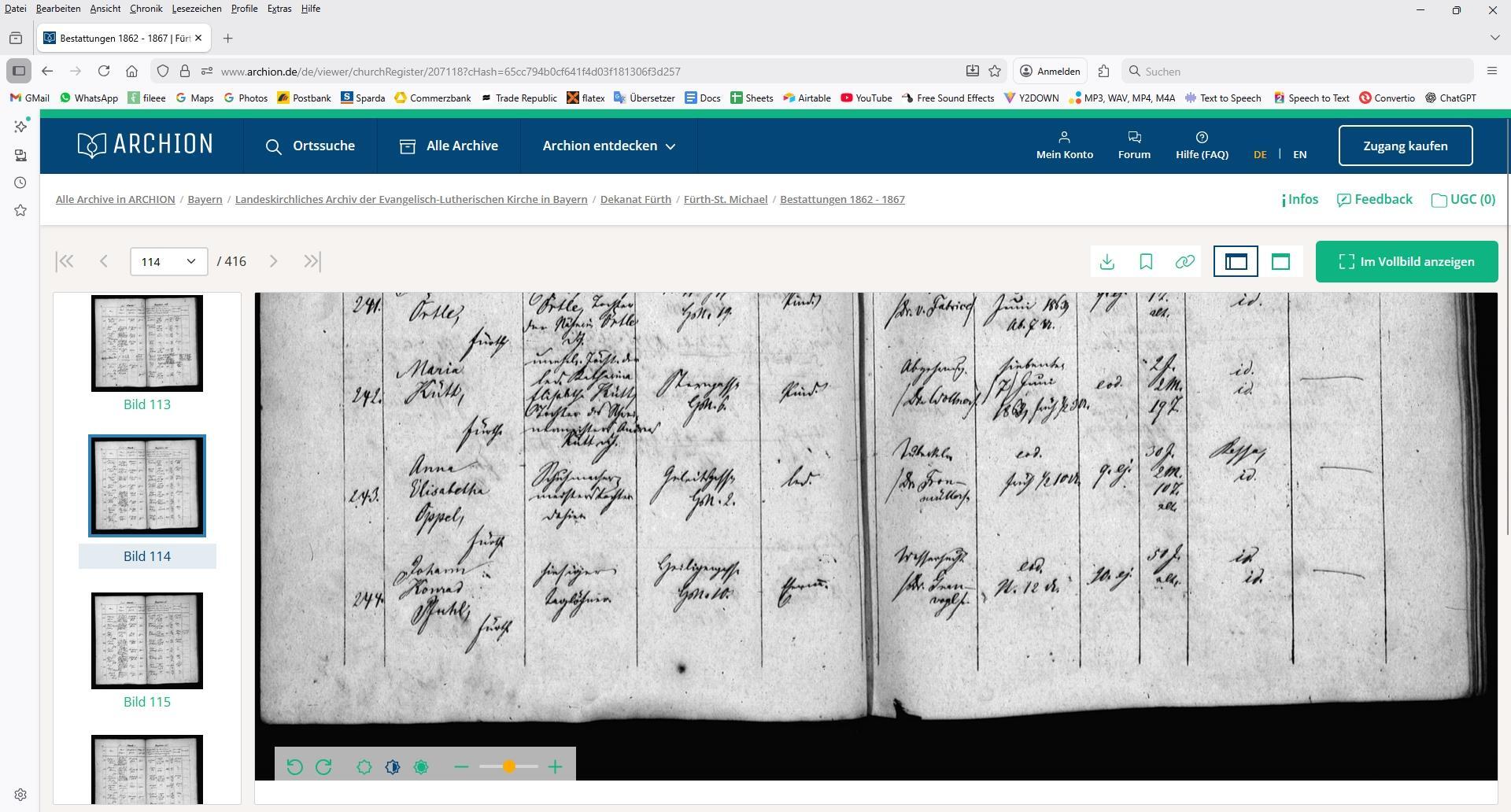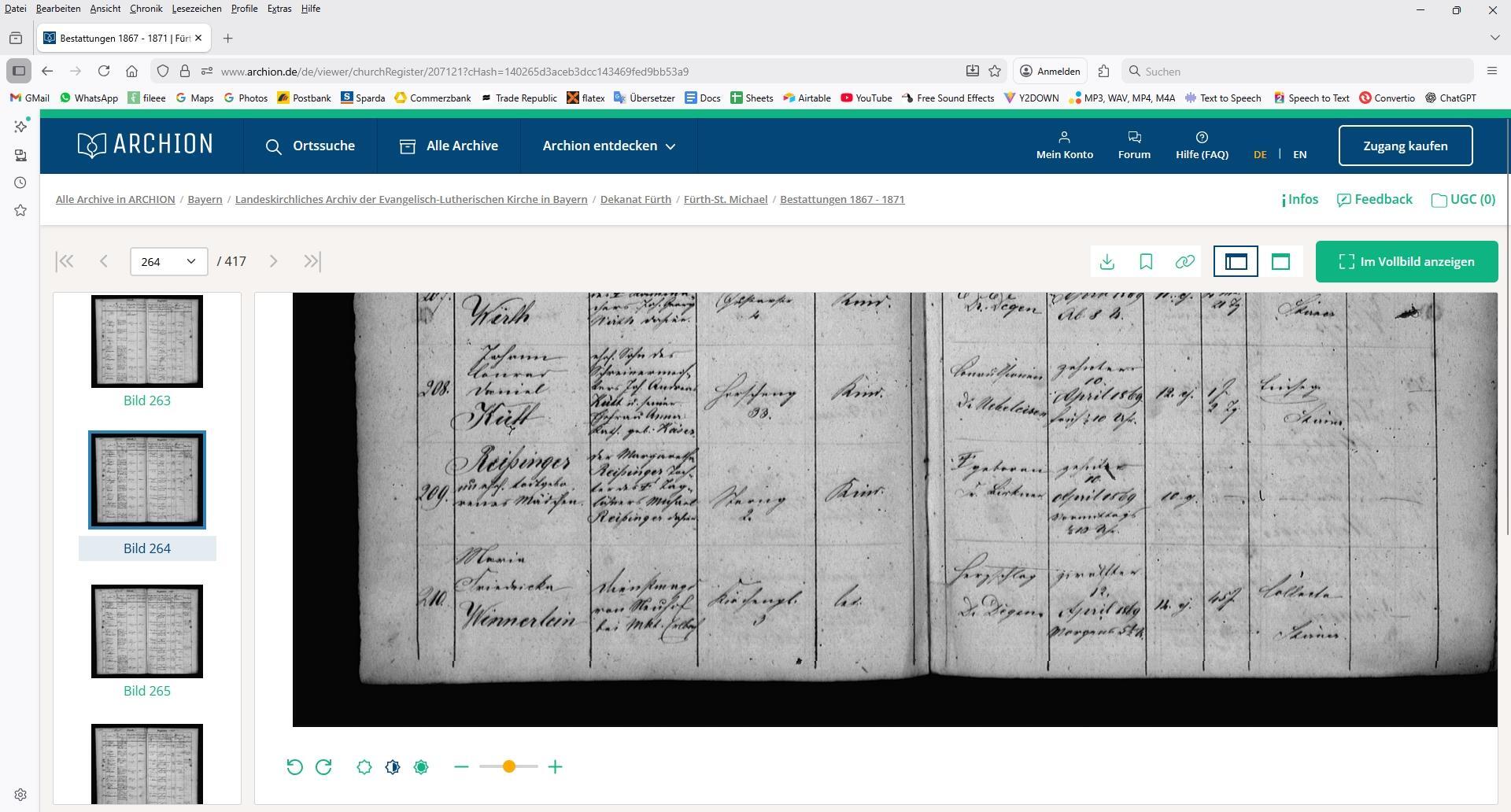
Würde mich über eine Übersetzung freuen (Bestattungen Fürth)
Bei der Zeile 208 fehlt mir der Starßenname und die Krankheit, die zum Ableben führte.
Bei der Zeile 242 kann ich nur bruckstückhaft lesen, dass es sich anscheinend um ein uneheliches Kind handelt.
242
unehel(iche) Tochter der led(igen) Katharina Elisabeth Kütt, Tochter des … Kütt … – beim Rest sind die Auflösung der Abbilung und meine Augen nicht kompatibel.
Ich vermute: des Schreinermeisters Andreas Kütt d.J.
Sterngasse [] 6 (die Abkürzung dazwischen kann ich nicht deuten; ein H am Anfang? steht es für so etwas wie Hinterhaus? ich kann die anderen Kringel nicht sinnvoll zuordnen)
Als Todesursache: Abzehrung
Bei 208 vermute ich: Hirscheng[asse] 33. (Das i sieht eher wie ein e aus; im FürthWiki gibt es aber einen Kütt, der 1871 unter dieser Adresse geboren wurde; könnte also trotzdem hinkommen).
Bei der Todesursache vermute ich Convulsionen.